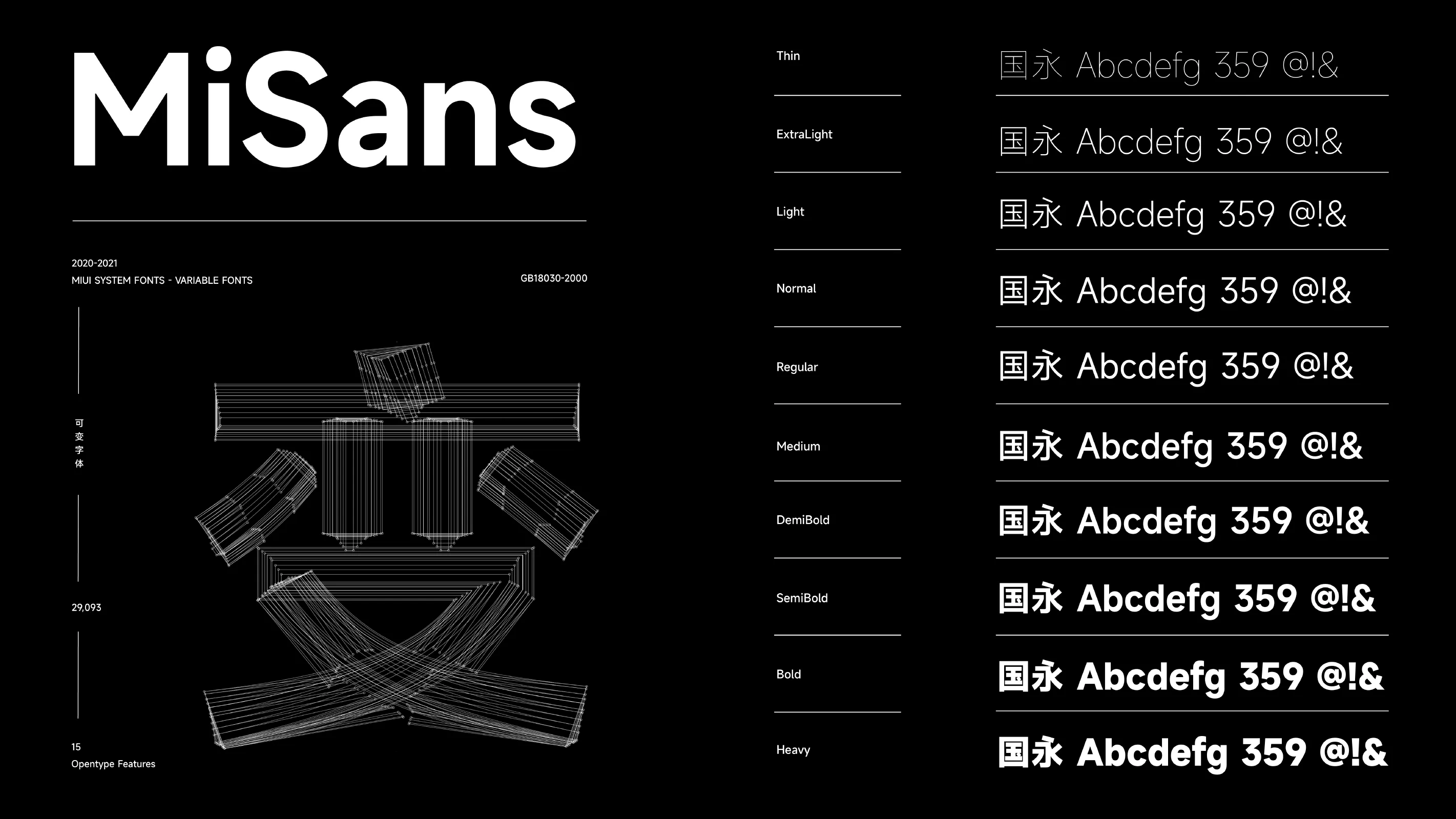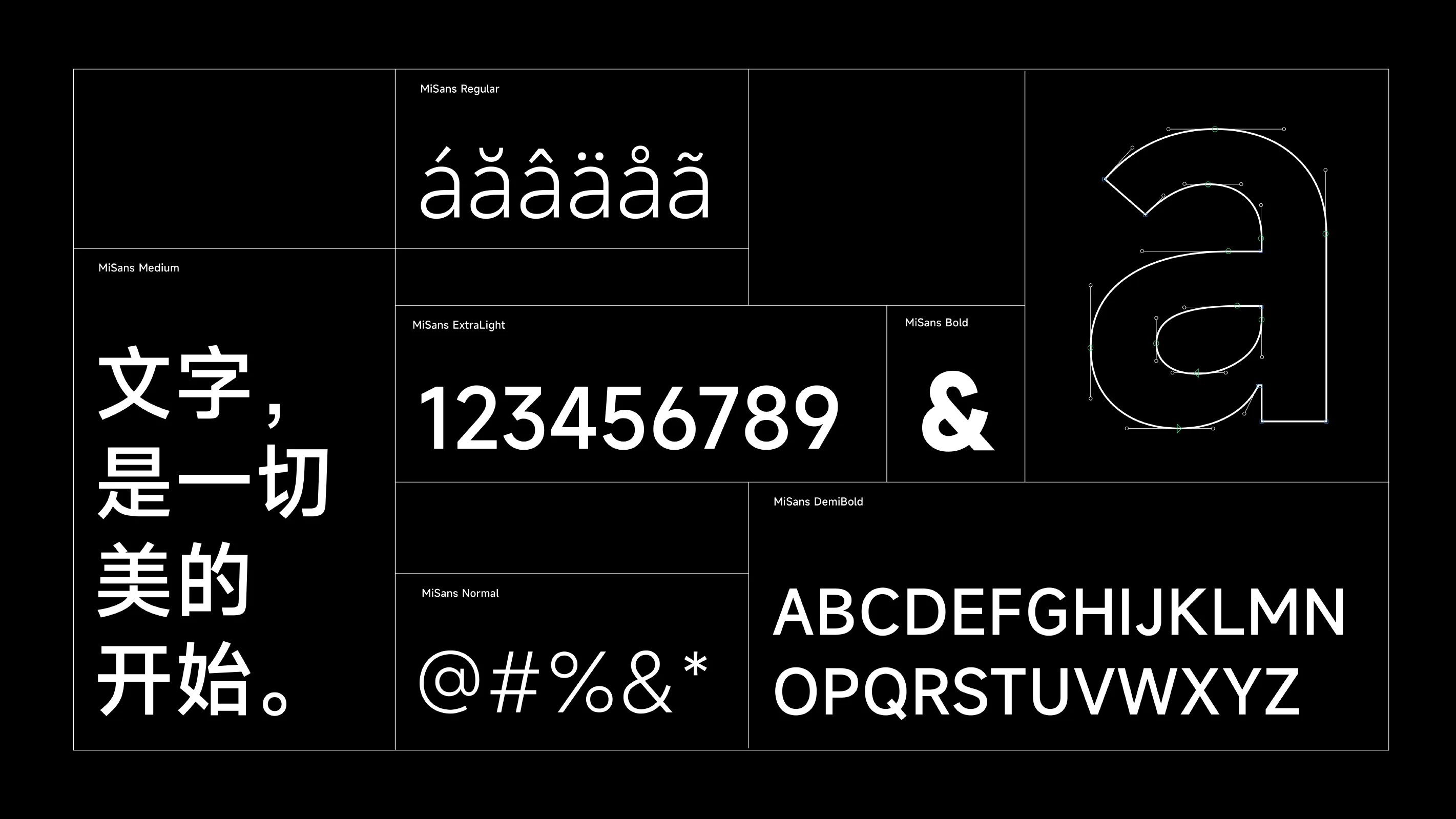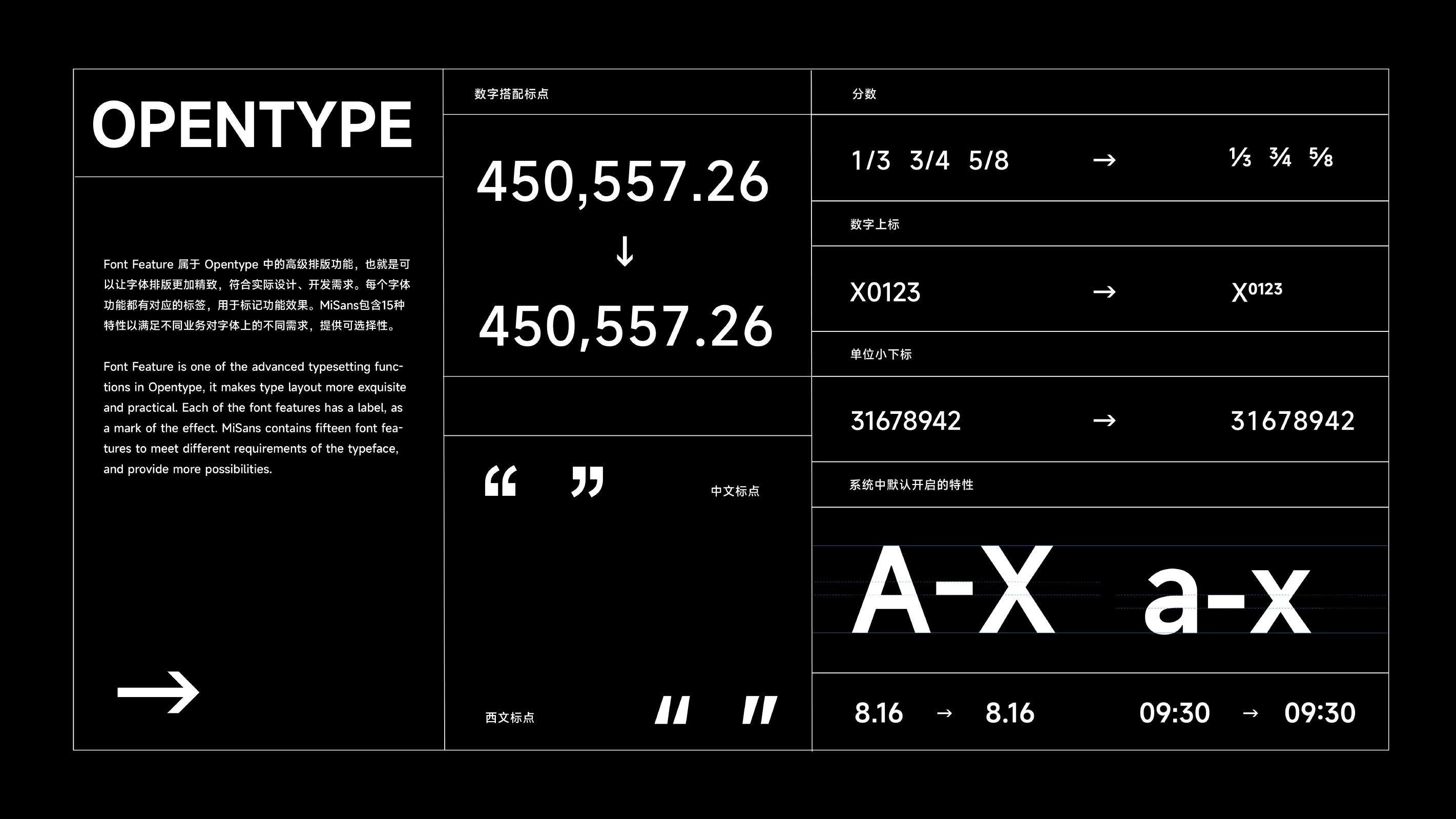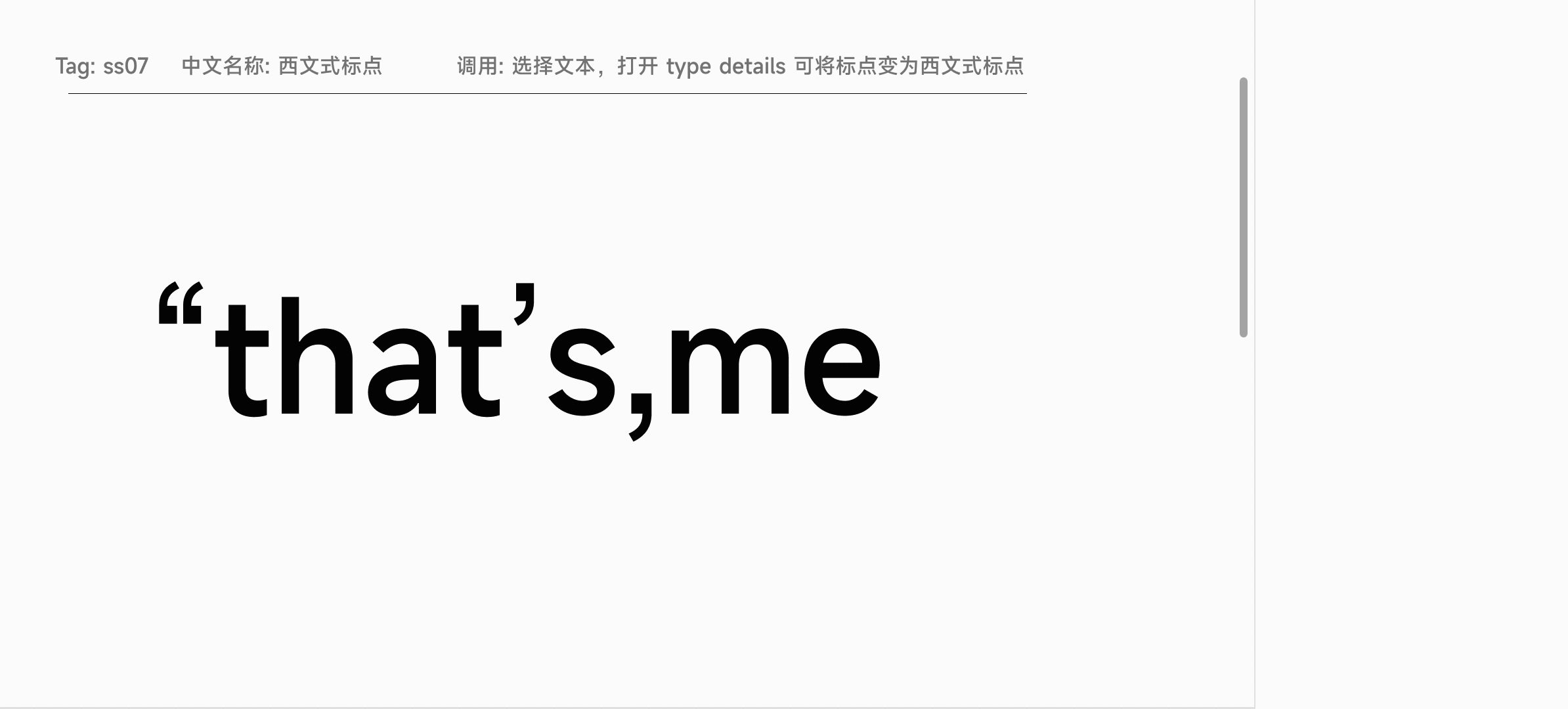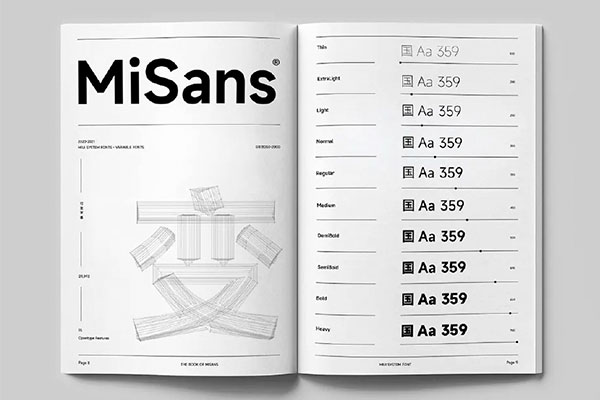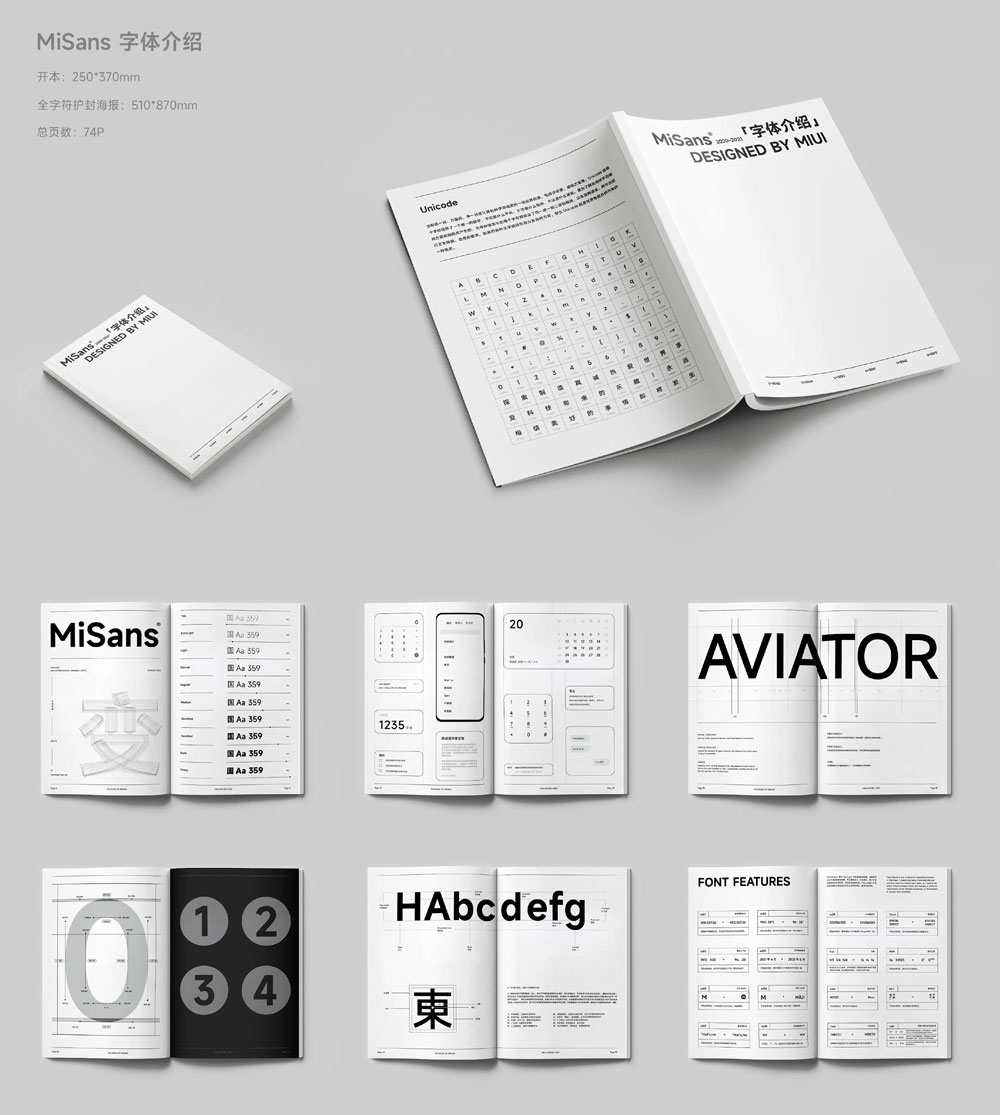
MiSans是小米公司最新推出的MIUI 13内置的全新系统字体,随系统一起发布,供全社会免费商用。
担心使用微软雅黑侵权的小伙伴有福了,现在微软雅黑有了新的替代字体,那就是MiSans。这种字体设计简约,笔型平直有力,视觉效果出色,特别适合屏幕显示。其字重齐全,层级清晰,拥有10个字重,实力大厂出品,质量无需怀疑。
MiSans共包含29,093个字符,支持多种语言。它还提供了多种OpenType功能,可以根据特定需求来选择不同形态的字符。例如,某些标点符号可以根据周围字母的形态自动调整至合适的位置。这种智能化的字体设计可以带来更好的阅读体验。
字体功能调用及实现
font-feature 属于 Opentype 中的高级排版功能,也就是可以让字体排版更加精致,符合实际设计、开发需求,可根据特定设计需求选择不同的字体形态。大部分软件都可以通过 Opentype 面板访问此功能。
(部分特性在MIUI系统应用中不会默认生效)